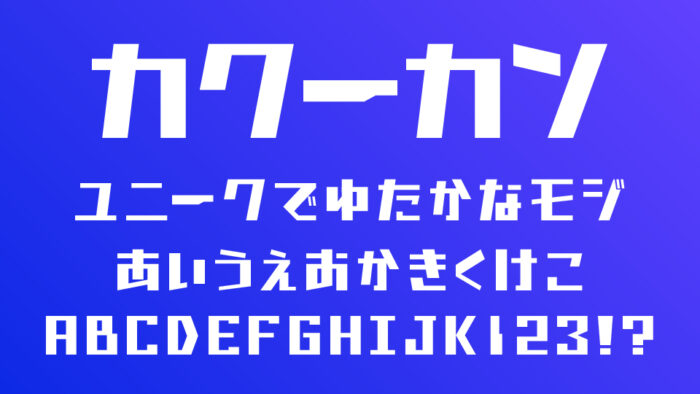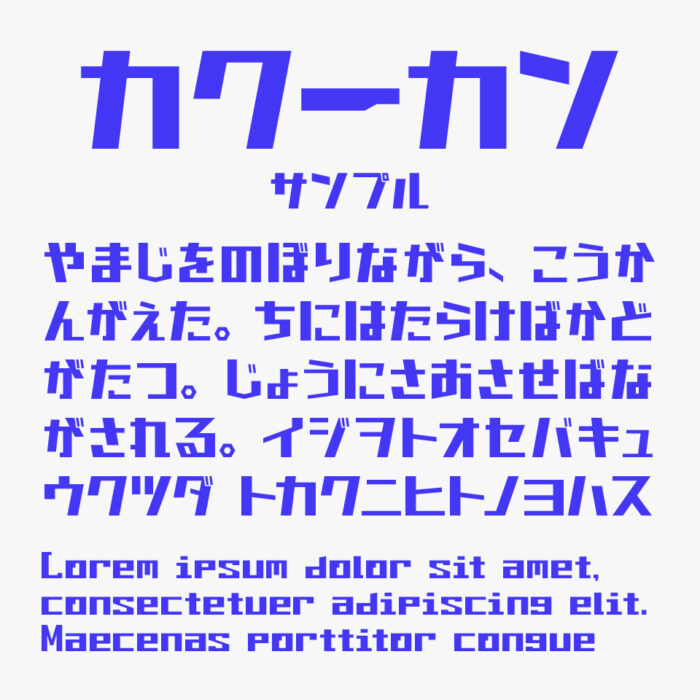
N4カクーカンV2フォントは、極端なカクカクとした角張りと均一な線幅が特徴のユニークなデザインフォントです。
昔のビデオゲームやポスターを思わせるような、アナログっぽい雰囲気ありつつ、大胆で個性的な直角的なフォルムが目を引くユニークなデザインとなっているフォントです。
どこか遊び心も感じさせるユニークな設計なので、タイトルロゴや見出しなどにもぴったりです。
N4カクーカンV2